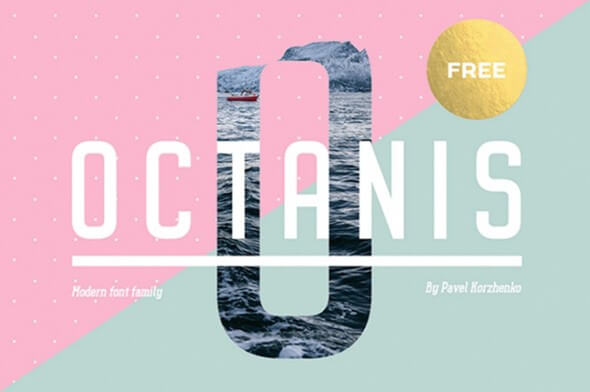
今流行のデザインでWEBサイトを最新にしたくはないですか?この記事ではモダンなデザインの印象的な無料フォントを厳選してご紹介しています。多くのスタイル、serifs,sans serifs,多様な線の太さ、太字、斜字体、標準、アクセントなどの素晴らしい書体で、プリントやデジタルプロジェクトを素敵に飾ることができます。
これらの美しく、印象的なフォントは間違えなくプロジェクトを際立たせることでしょう。ポスター、雑誌、電子書籍、チラシ、タイトル、ロゴ、本文など用途も多岐にわたります。さらに、これらのフォントは無料ダウンロードをして使えるのです。サイズに関係なく様々なプロジェクトをおしゃれに飾る高品質のアイテムです。
ここでは最新トレンドでおしゃれな無料フォントを20個厳選しています。あなたの想像力を刺激するようなお気に入りのフォントが見つかると良いですね。
Gorgeous: A free elegant typeface in 12 weights
Rajesh Rajputによる美しいsans-serif書体です。小文字、大文字、句読点、アクセント、数字の385のグリフと12の無料ウェイトが含まれています。
Peenu: A free hand knitted typeface
Peenuは大文字限定のフォントで無料ダウンロードが可能。様々なデザインプロジェクトに使用できます。この無料サンプルはクリーンなデザインで、見出し、ポスター、チラシなどを素敵に実装させます。
Knox Regular: A font inspired by American western culture
この豪華な書体はMcraftによって作成発行されました。このフォントはアメリカの西部文化をインスピレーションに、ビンテージデザインに使用しています。
Hal: A free typeface inspired by A Space Odyssey
Aganè: A free font designed for UIs
Aganèは読みやすいためUIデザインに最適なデザインです。あなたのプロジェクトに使用できるかよく見て確認してください。
SUNN: A free set of 3 hand-drawn fonts
Sunnは手描きが美しい3つのフォントを編集した作品です。これらはそれぞれSunn line, Sunn serif, and Sunn line serifと言います。
Cheque: A free font with vintage look
Chequeは幾何学的な形とヴィンテージな見た目の美しい無料フォントです。この無料サンプルは見出しに最適なデザインです。
Cabo Slab & Cabo Rounded: 4 free font styles
Cabo slabとCabo roundedはDesign a LotのBogdan Cașotă によるデザインの2つの素敵なフォントファミリーです。Helveticaをインスピレーションに作られています。
Priscilla: A free calligraphic font
Priscillaは IanMikraz Studioによって作られた美しい書体です。この無料サンプルは新鮮なデザインで多くのデジタルまた紙媒体のプロジェクトに最適です。
Fira Sans: A new free font family by Mozilla
新鮮でモダンだデザインの素晴らしい書体です。現在の、また今後のプロジェクトにどうですか?
Noto Sans: A free typeface supporting 800+ languages
Noto sans は多様なスタイルやウェイトを含む無料フォントです。この素晴らしいフォントをあなたにデザインに加えてみませんか?
Cassannet Plus Regular: A free font for vintage typography
Cassannet Plusは6つのスタイルを持つヴィンテージなデザインの書体です。どんなプロジェクトにも合い、目を引くデザインとなっています。
Migur: A free elegant serif font
Migurは上品なSerifデザインのモダンな書体で、ロゴタイプコンセプトに最適です。あなたの条件に合うかよく見てみてください。
Typewalk Mono 1915: A vintage typewriter grotesque font
Typewalk Mono 1915は無料でダウンロードと使用が可能です。このヴィンテージな見た目は小規模のプロジェクトに最適で、オンラインプロジェクトを美しく飾ります。
Knucklehead Regular: Vintage style free font
Knuckleheadはデジタルにも紙媒体のプロジェクトどちらにも使える素敵なデザインのヴィンテージな書体です。こちらも無料ダウウンロード、使用が可能です。
Octanis: A full and free font-family ideal for headlines
Octanisは無料でダウンロード、使用可能な素晴らしいフォントファミリーです。見出しやロゴタイプに使えます。
Somatic Rounded: A free font ideal for logotypes
Somatic roundedはシンプルかつ効果的なデザインの素晴らしい書体です。現在作成中また、これからのプロジェクトに加えてはいかがですか?
Kadisoka: A free calligraphy font for beautiful typography
Kadisoka script は素晴らしい手描きのデザインでロゴタイプや見出しに最適です。
Buffalo: Free monoline script font
Buffaloは美しく個性的な丸みを帯びたデザインです。これも無料でダウンロード、使用が可能です。
Mueller Narrow: 4 Free font styles
Muller narrowは20のウェイトを持つ無料ダウンロード可能な書体です。このモダンな書体はどんなプロジェクトにも使えるデザインです。